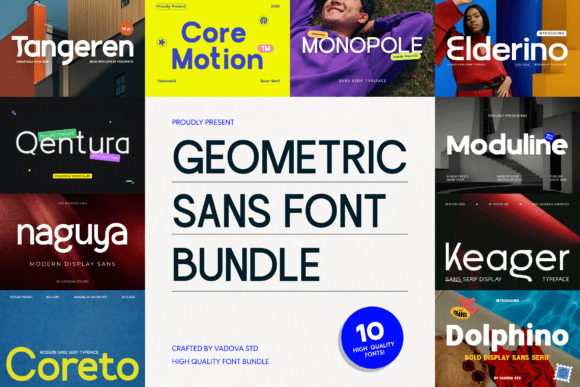
Geometric Sans Bundle
หากคุณกำลังมองหาเนื้อหาคุณภาพสูงเช่น Geometric Sans Bundle แพ็คเกจพรีเมียมนี้เป็นตัวเลือกที่ยอดเยี่ยมสำหรับโปรเจ็กต์สร้างสรรค์ของคุณ